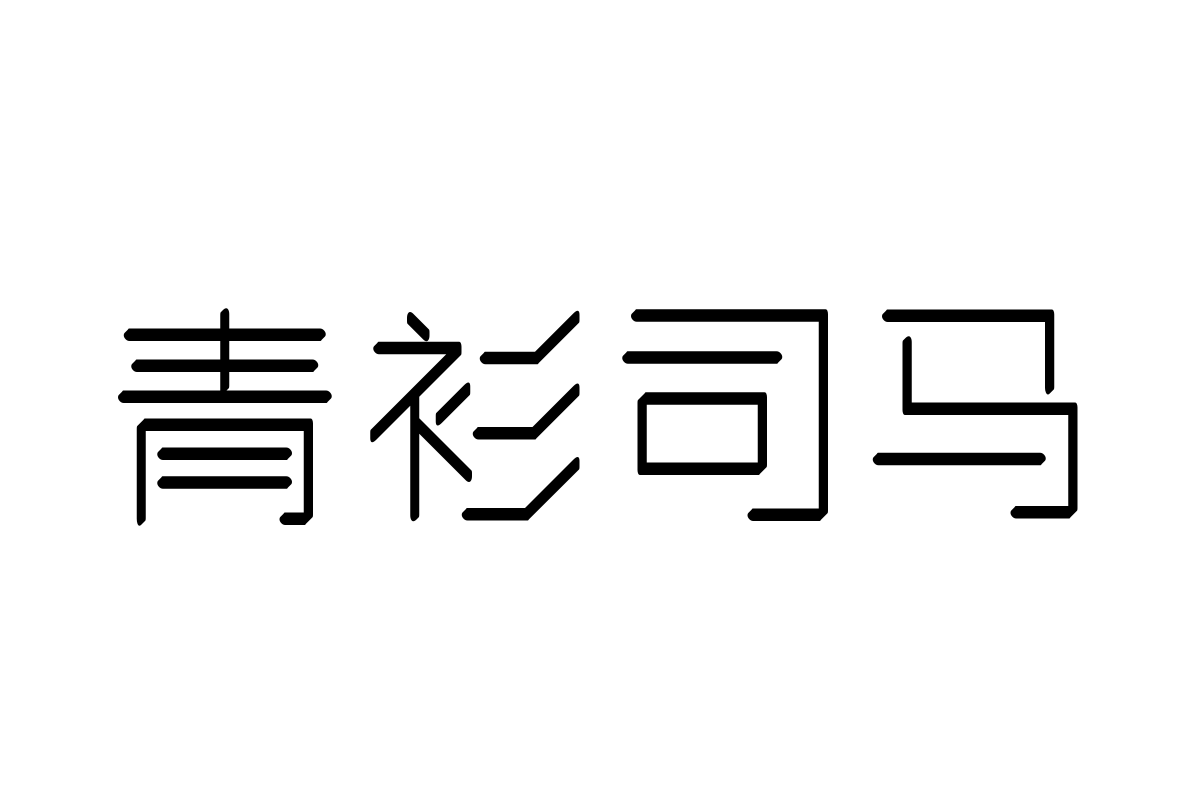
三极纤云是一款具有现代感和科技感的字体,它采用了独特的设计元素,使得整体看起来更加简洁、大方。这种字体适合用于各种商业、科技、广告等场合,能够很好地吸引人们的注意力。
在字形设计上,三极纤云采用了简约的风格,线条流畅,没有过多的装饰和修饰。这使得整个字体看起来更加清晰、易读,同时也能够更好地传达出品牌的形象和理念。
此外,三极纤云还具有一定的可塑性,可以根据不同的应用场景进行适当的调整和变化。这使得它不仅适用于传统的印刷媒体,也非常适合应用于数字媒体和网络平台,如网站、移动应用等。
总之,三极纤云是一款非常实用的字体,无论是在视觉传达还是品牌塑造方面都表现出色。